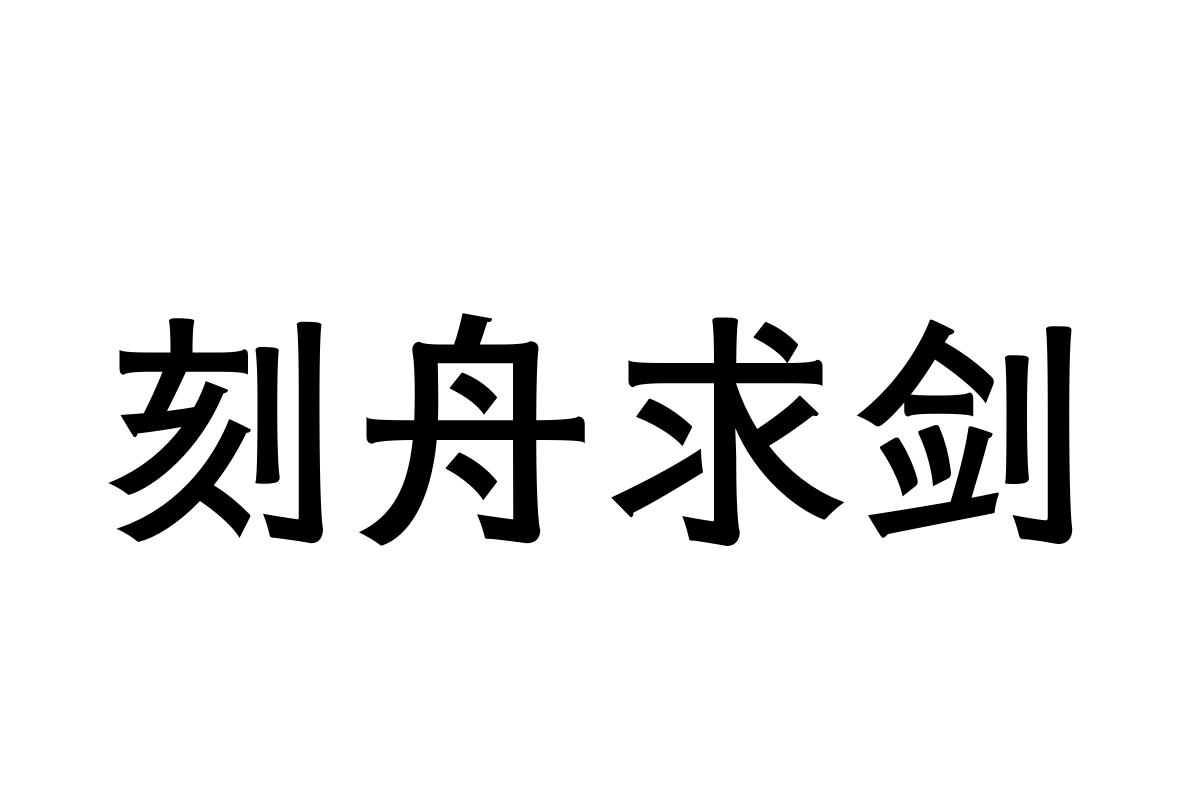
汉仪云黑65w是一款现代简约风格的中文字体,具有独特的设计特点。这款字体采用简洁的线条勾勒出每个字符的形状,使得整体看起来非常清晰、易读。同时,它又不失优雅和时尚感,非常适合用于各种需要展示文字内容的场合。
汉仪云黑65w的特点包括:
– 字形规整:每个字符都经过精心设计,确保字形规整、易于识别。
– 风格简约:线条流畅,没有过多的装饰元素,给人一种简约而现代的感觉。
总之,汉仪云黑65w是一款非常实用的中文字体,适合用于各种需要展示文字内容的场合。